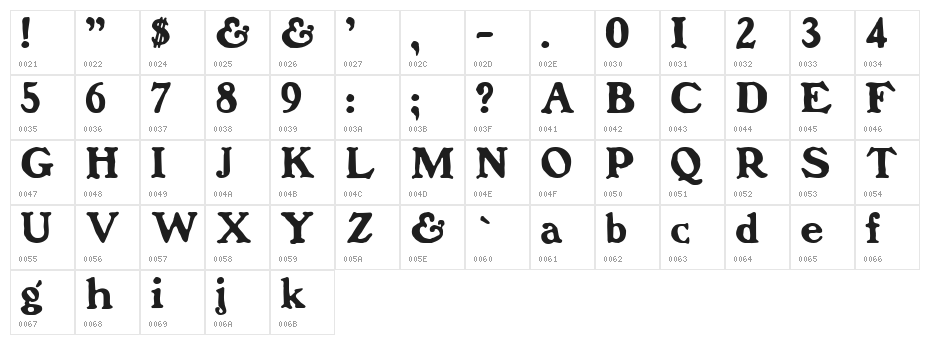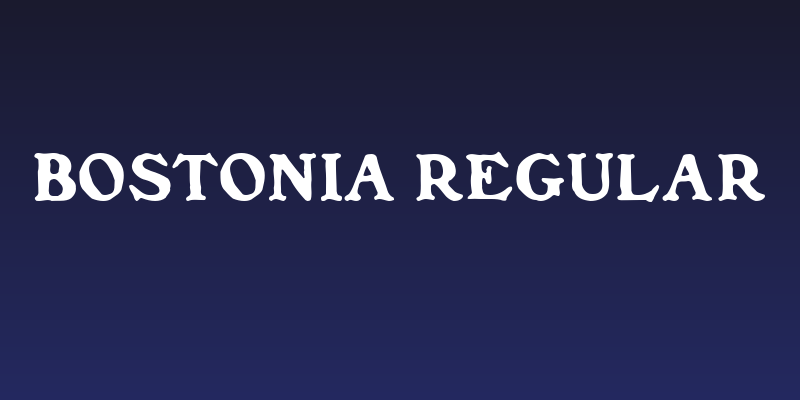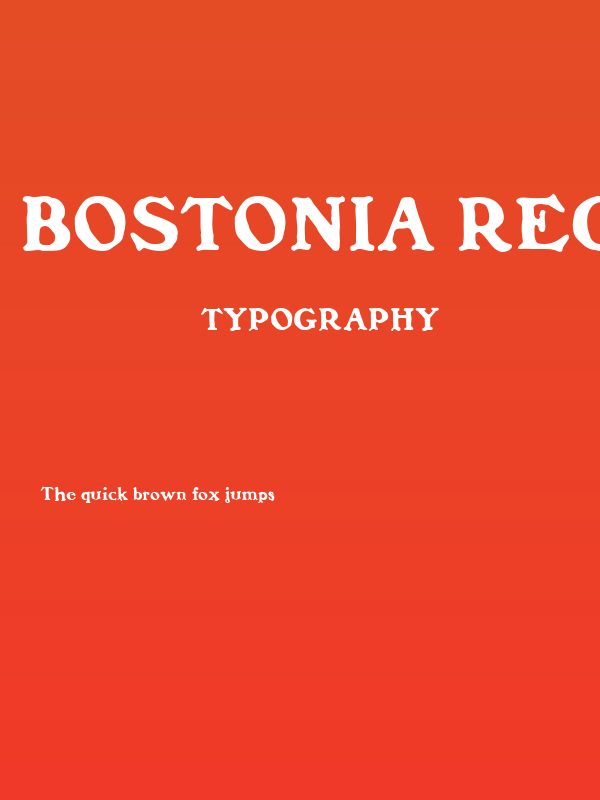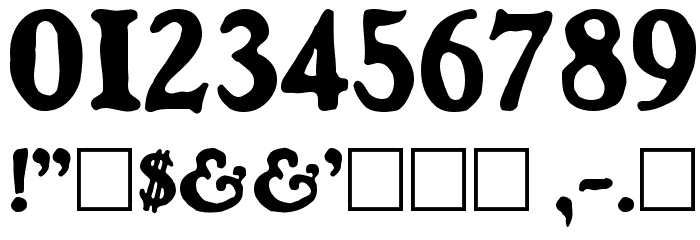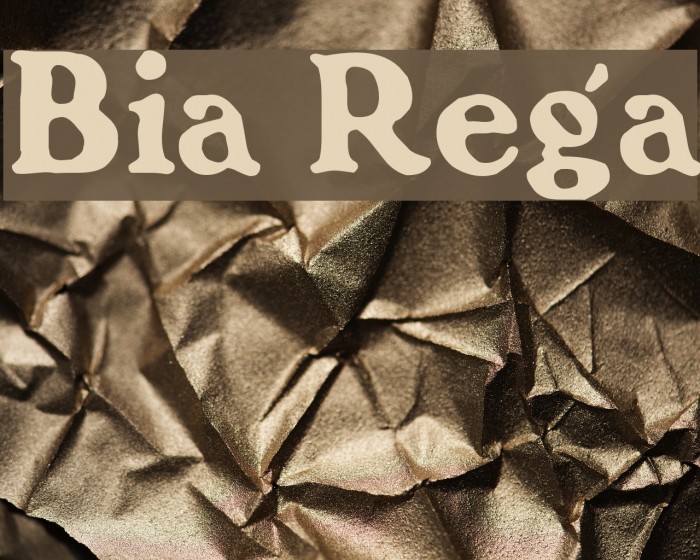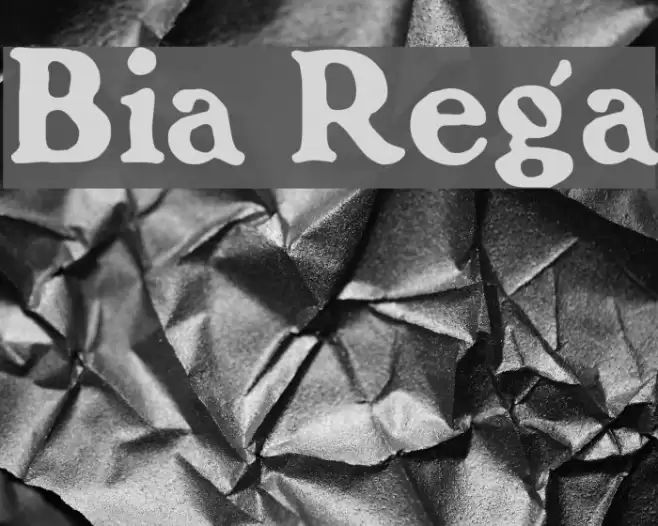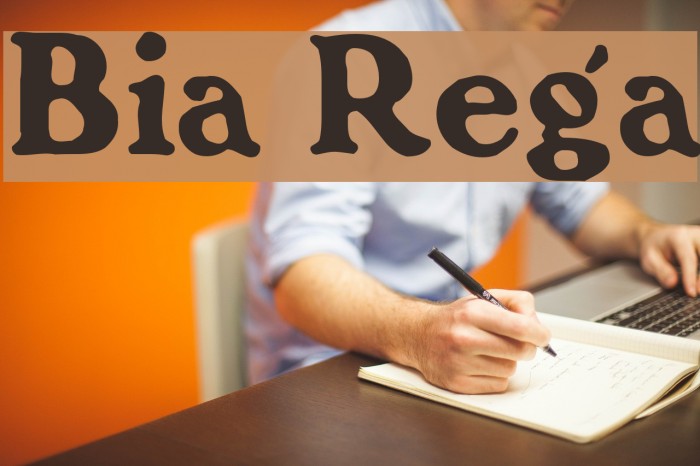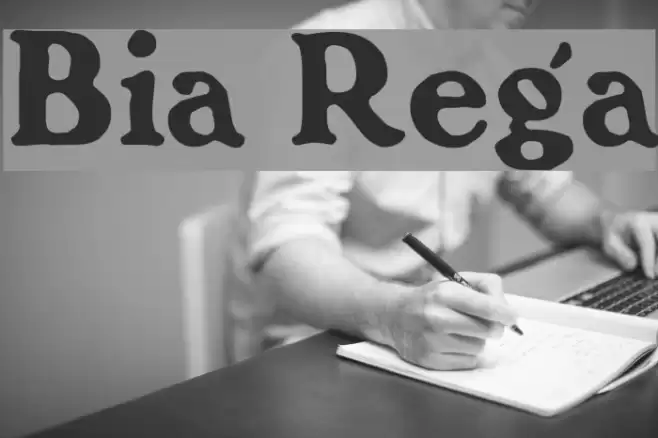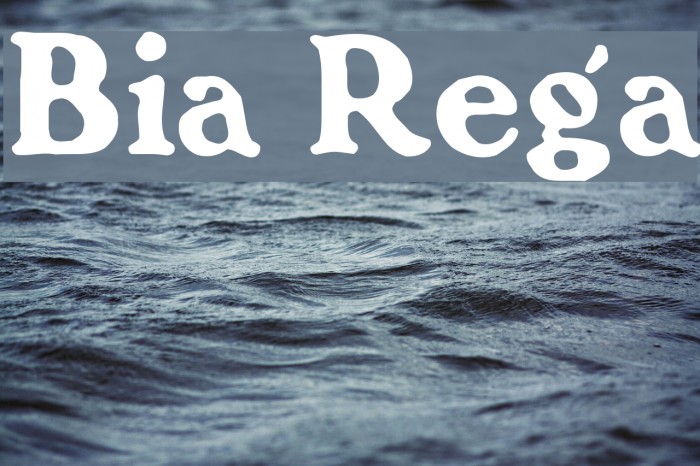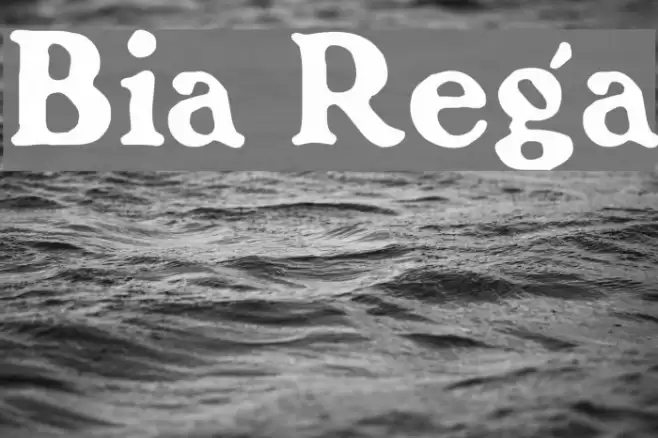
Bostonia Regular Font
| Progetti proposti | Ideal for vintage-themed posters, branding, book covers, and any project seeking a classic, old-world aesthetic. |